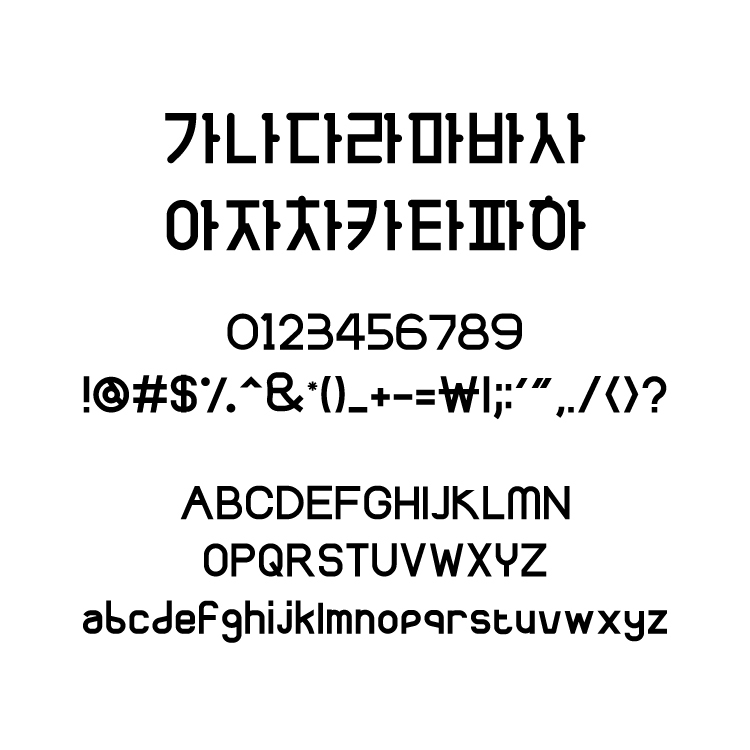
소개
한글날을 기념해 의미있게 오픈한 다람쥐 꼬리를 닮은 개성있는 서체입니다. 박스테이프와 벽에기댄체 라는 두가지 폰트도 함께 아래 출처 링크를 통해 확인 하실 수 있으니 참고하세요 :)
(다람쥐꼬리체는 포토샵의 자체 폰트 볼드기능을 이용할 경우 받침이 뭉개지는 현상이 있으니 원본 그대로 사용할 것을 추천드립니다)